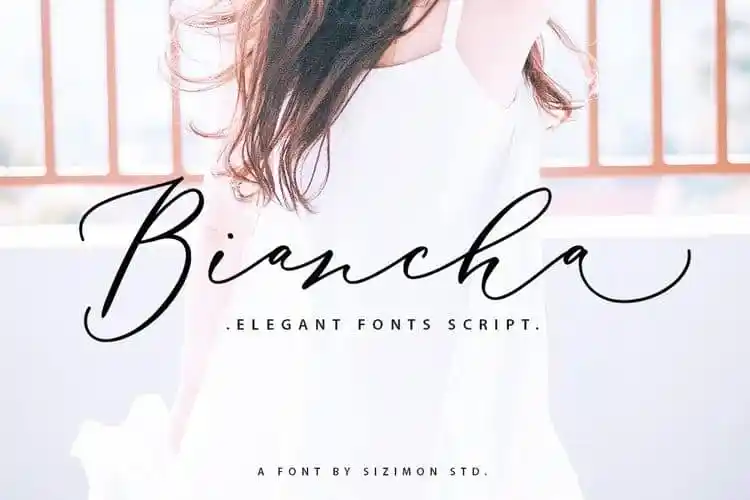
Biancha Script Font é uma escolha perfeita para quem procura uma fonte de script elegante e charmosa. Introduzida pelo designer sizimon através do site 99designs, Biancha possui traços finos, femininos e descontraídos. Seu design casual e rápido inclui muitas ligaturas, criando um estilo único que combina facilidade de uso com elegância. Perfeita para estilos fashionistas ou blogs de tendência, Biancha também é ideal para marcas de e-commerces desejosos de transmitir sofisticação e elegância. Seja em sua forma mais formal ou descontraída, a fonte Biancha mantém seu charme, fazendo com que qualquer projeto apresentado seja irresistivelmente atrativo e sofisticado.